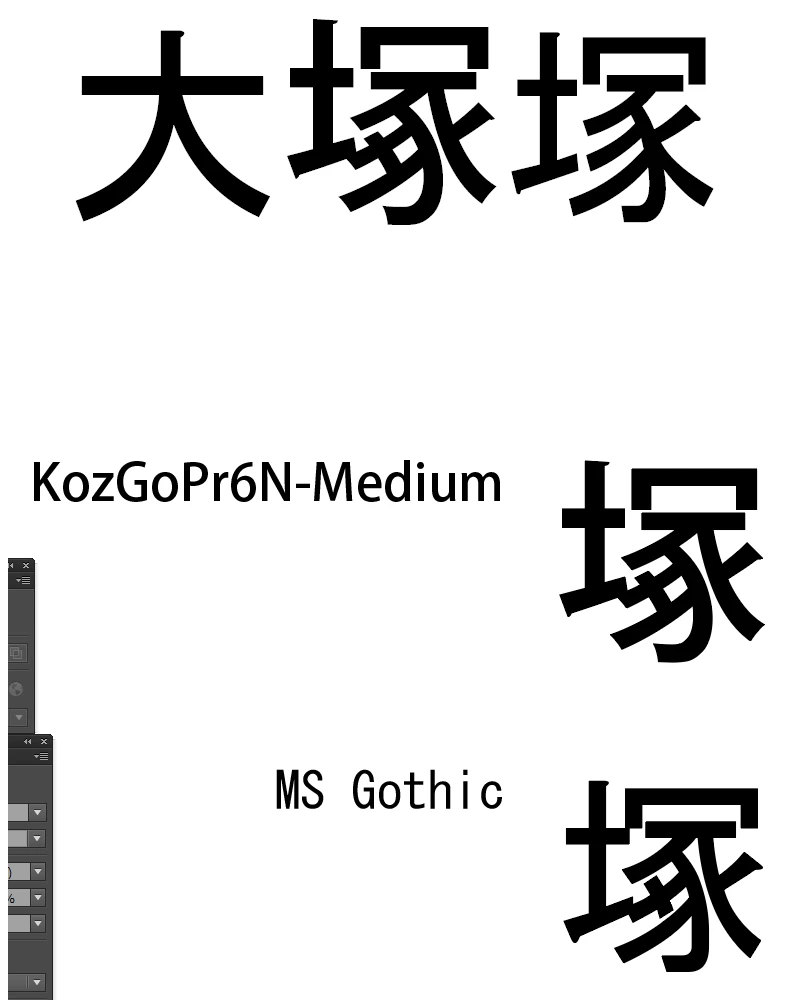
Adobe Reader XI (バージョン:11.0.18)でフォント埋め込み無しで外字を表示する場合にある文字のみが太字で表示されます。
6文字(塚塚葛灘溝梢)をPDF表示する際に
「塚(U+FA10)」のみ太字で表示されます。
【PDFの作成条件】
・元の6文字のフォントは、MSゴシックを用意
・“フォントの埋め込みなし”でPDF作成実施
PDF表示時に「塚」のみが違うフォントファイル
を参照しているということでしょうか?
頂いた画像を拝見いたしましたが、小塚ゴシックの字体となっていること確認いたしました。
なぜ、「塚(U+FA10)」がMSゴシックではなく小塚ゴシックの字体となるかについては
理由はわからず仕様であると思うしかないのでしょうね。。。
> おそらくなんですが、UnicodeのCJK互換漢字に対する処理で何か影響が出ているのだろうと思いますが、・・・
> ただ埋め込みしていないものになるので、フォント表示はAcrobat/Reader等のPDFビューアーの処理に依存するので、・・・
IBM拡張文字(塚(U+FA10))以外(髙/高 﨑/崎 閒/間)でも実施してみましたが、(塚(U+FA10))のみが
やはり太字(小塚ゴシックの字体)となります。この事の原因に関する情報お持ちでしたら
共有頂けますと幸いです。
追加で確認したのですが、「﨑」(u+fa11)はやはり小塚が利用されるようです。
他にもいくつか、IBM拡張扱いの文字を確認しました(﨎/u+fa0e、鶴/u+fa2d、晴/u+fa12)が、
これらはMSゴシックが使用されました。
IBM拡張でもすべてがUnicodeのCJK互換漢字ではないので、そこに紐づくものとして
選定して推測しましたが、いまいちはっきりしないというのが実際のところです。
ただこれは、先般と同様、オリジナルが必要であれば埋め込みするしかない訳ですし、
埋め込みしていない場合の代替についてはコントロール不可能ですから、
「そのようなもの」と割り切るのが一番早いです。
確認したところ、どうやらAcrobatのフォルダー内に含まれる小塚ゴシック Mを参照しているようです。
下記、比較用に画像を作りました。
上側は、Word 2013で作成し、最小ファイルサイズ(埋め込みさせない)としてからAcrobatで表示されたもの。
下側がIllustratorで作成した、小塚ゴシックMとMSゴシックの「塚」(u+fa10)です。
比較すると、明らかに小塚ゴシックとなっているのがわかります。
おそらくなんですが、UnicodeのCJK互換漢字に対する処理で何か影響が出ているのだろうと思いますが、
プロパティで見ても小塚としての表示はないので、判断がつきづらいです。
ただ埋め込みしていないものになるので、フォント表示はAcrobat/Reader等のPDFビューアーの処理に依存するので、
これはある意味、仕方のないところだとは思います。
オリジナルと同じ表示をしたい場合は埋め込むしかないだろうと思います。